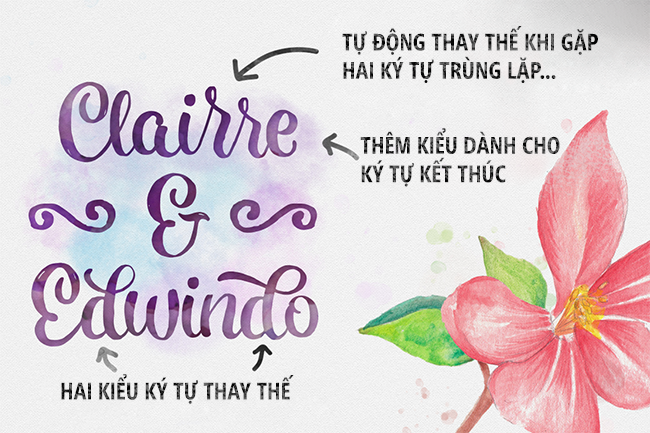
Hollycakes là một font chữ mới được tạo ra từ cọ vẽ và màu nước, được thiết kế thủ công để tạo ra sự hoàn hảo và tự nhiên của màu nước. Thích hợp cho nhiều mục đích: in thiệp, áo thun, logo, poster,…
Font hỗ trợ tính năng OpenType: Contextual Alternates, Stylistic Alternates và Contextual Swash. Bạn cần các chương trình hỗ trợ như Illustrator hoặc Indesign, Photoshop (hỗ trợ không đầy đủ).
Nhà thiết kế: Adam Fathony